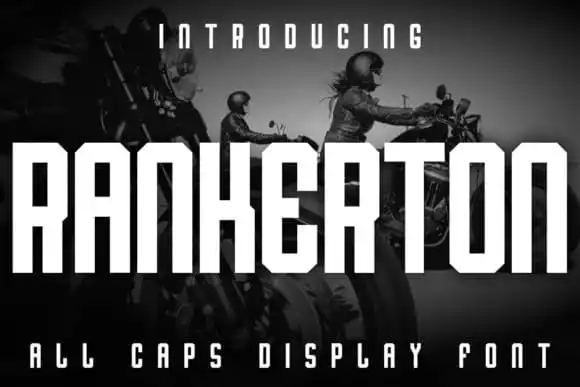
Rankerton Display Font é uma elegante fonte de exibição que traz letras maiúsculas, números e uma grande variedade de pontuação para criar visuais chamativos. Esta sans serif apresenta um estilo moderno, criado pelo designer de fontes de 99designs conhecido como deedeetype. A Rankerton Display é robusta e autêntica, ideal para trabalhos que exigem destaque visual agressivo, desde postais até ilustrações e selos. Ela celebra formas geométricas e estilos alternativos em seu aspecto único, tornando qualquer projeto mais vibrante e criativo. Com a Rankerton Display, suas ideias podem se transformar em arte vivida, dando vida às mais inusitadas criações gráficas. Esta fonte é perfeitamente adaptada para aplicações como postais, design web, marcação, ilustração, selos e muitos outros trabalhos que precisam de destaque e personalidade.